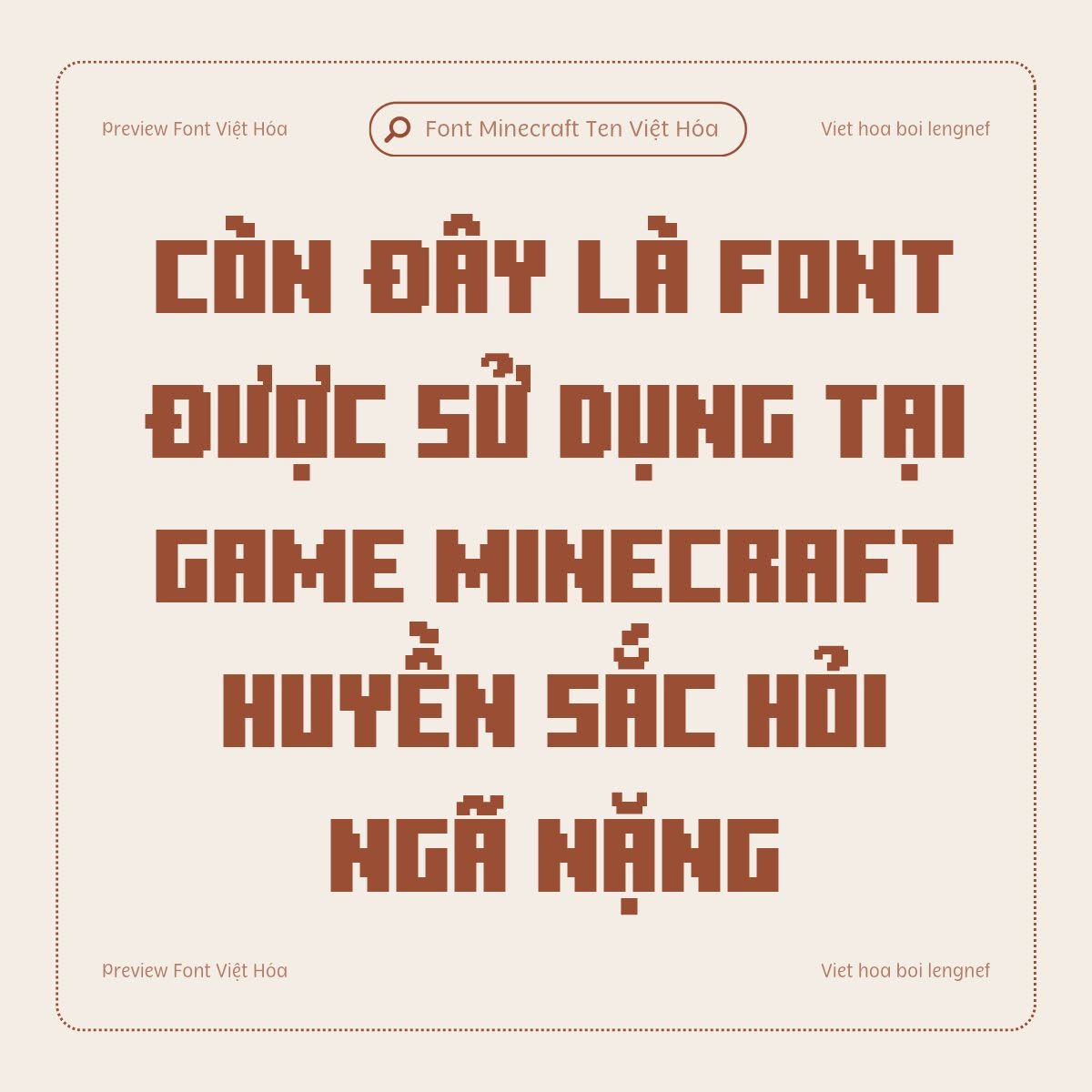
Việt hóa theo yêu cầu 16 || LF Minecraft Ten
- Tác giả: KendroType
- Việt hóa: lengnef
Minecraft Ten là phông chữ dành riêng cho game Minecraft. Từng ký tự được tạo bởi những ô vuông đặc trưng của game tạo nên cảm giác mạnh mẽ. Phông này phù hợp để thiết kế tiêu đề, banner, logo hoặc các dự án liên quan đến game, công nghệ…